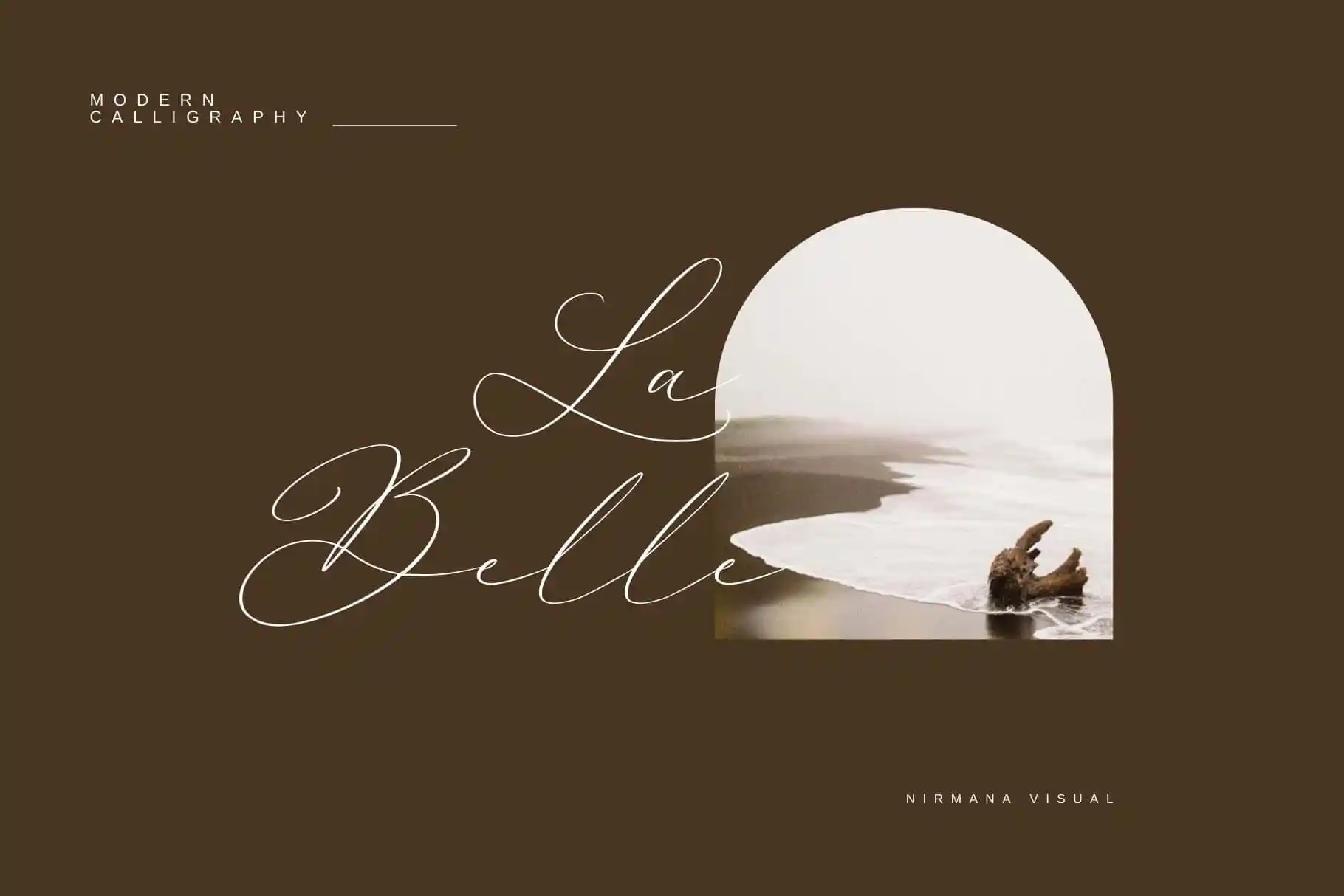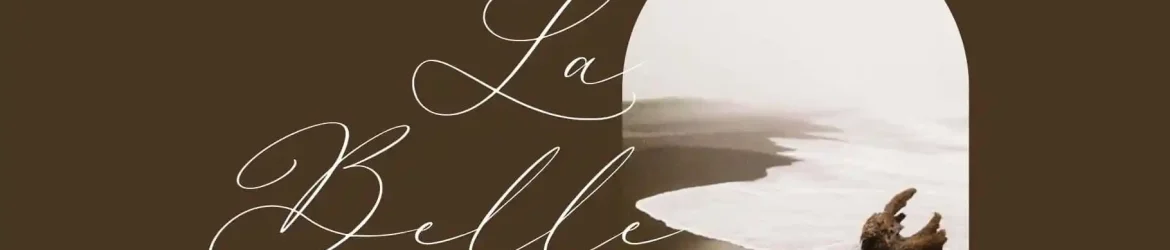
La Belle Font é uma elegante tipografia moderna criada pela Nirmana Visual. Esta fonte traz a sofisticação clássica combinada com a autenticidade das escritas antiguinhas, oferecendo um mix perfeito de beleza e profissionalismo. Suas linhas suaves e harmoniosas garantem que as suas criações sejam instantaneamente atraentes e chamativas. Ideal para designers em busca de uma opção moderna para criar designs variados como anúncios, textos nas redes sociais, identidades corporativas, logotipos e até mesmo posters, La Belle Font irá ajudar você a dar um salto imediato no seu portfolio profissional. Experimente agora e comece a transformar suas criações em verdadeiros destaques.